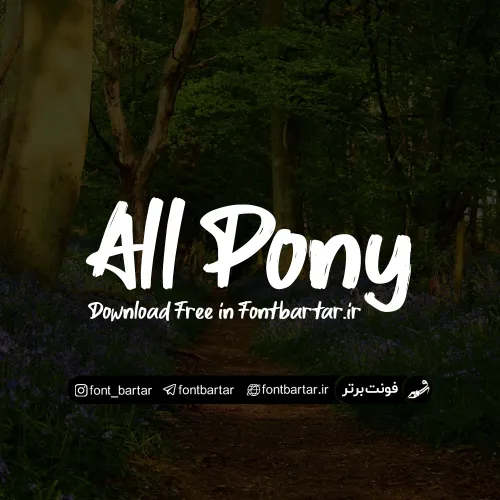
فونت انگلیسی All Pony
فونت انگلیسی All Pony ، دارای بافت براش یا جوهری ساختار پیچیده و خاص یکی از فونت های پرطرفدار لاتین است که از دسته فونت های گرافیکی پرکاربرد می باشد ، مناسب طراحی لوگو و طراحی تایپوگرافی لازم به توضیح است این فونت در دو فرمت هم اکنون بصورت رایگان از فونت برتر در دسترس شماست ، لذت ببرید.
فونت All Pony مورد استفاده برای:
• طراحان وب سایت و گرافیست های خلاق می توانند از این مجموعه زیبا فونت در طراحی پروژه های تبلیغاتی و تجاری خود کمک بگیرند.